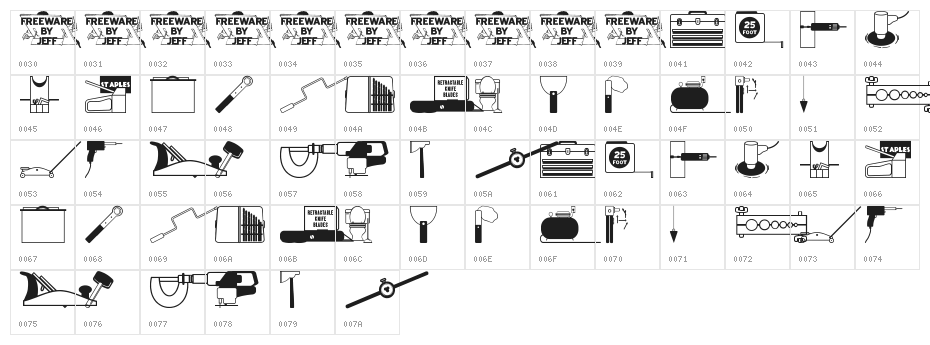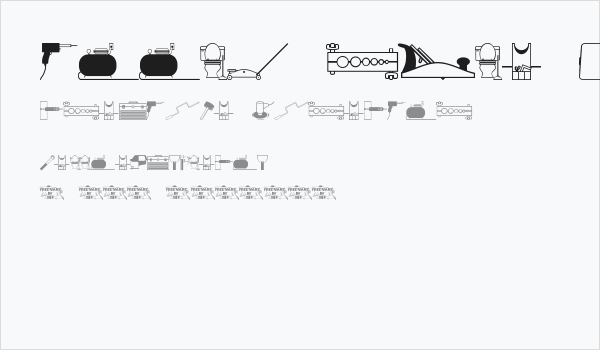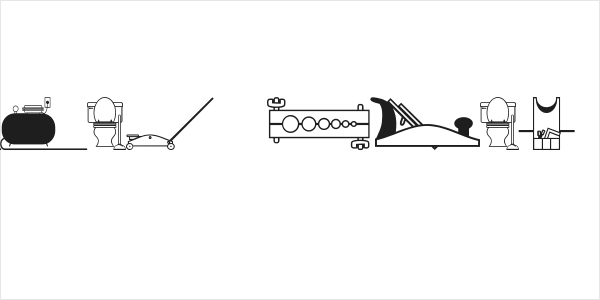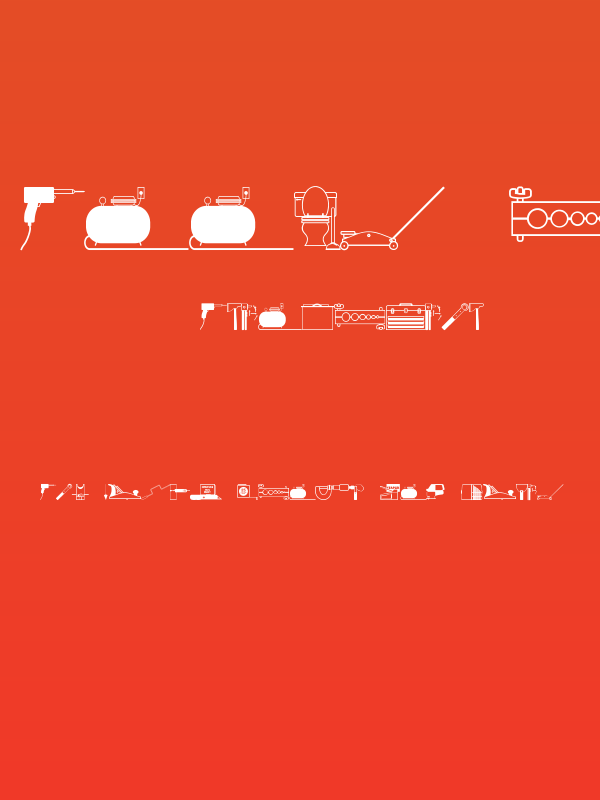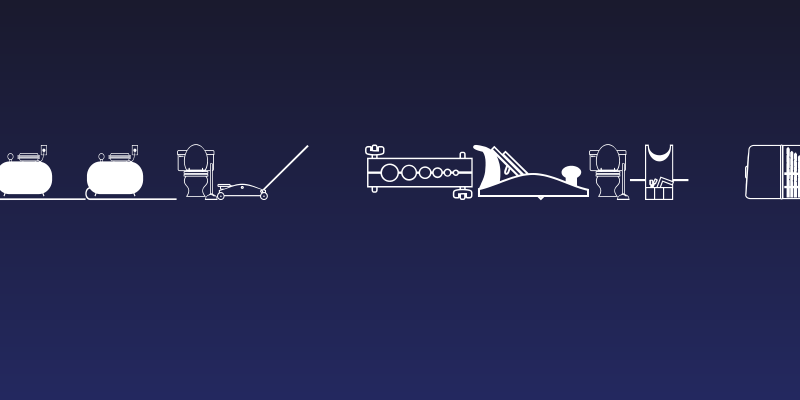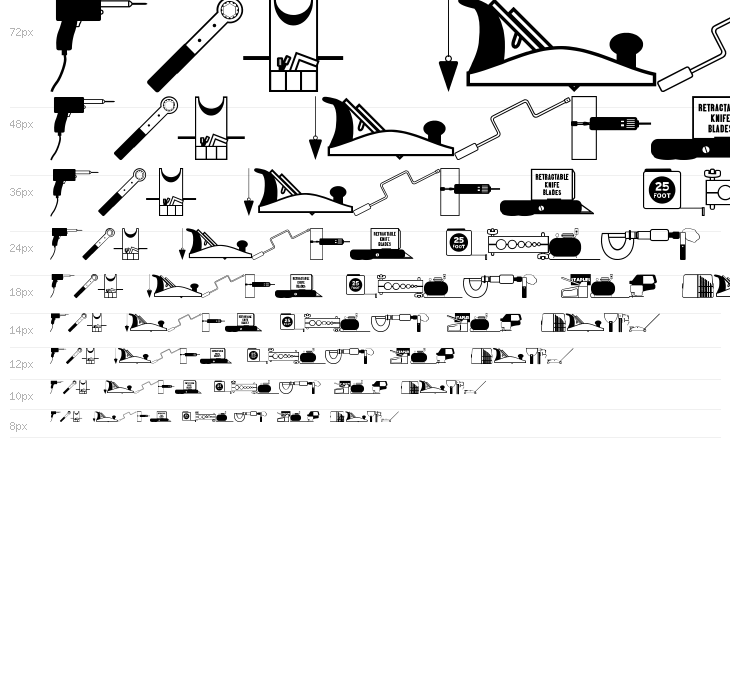
Tools Rule! JL Font
| 用途 | Logos, Posters, Educational Materials |
| おすすめプロジェクト | Ideal for industrial-themed designs, educational materials about tools, or creative projects requiring a mechanical aesthetic. |